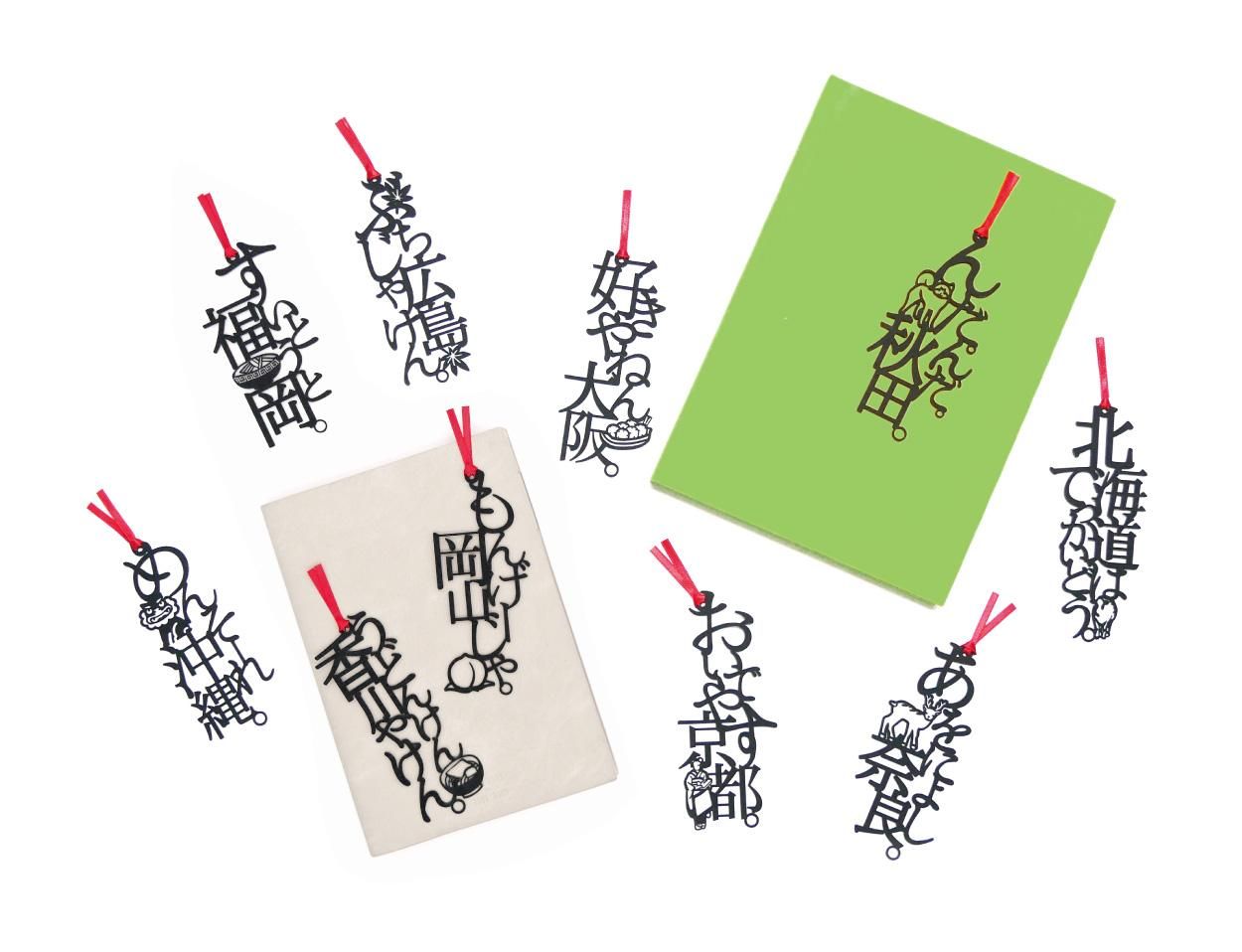
文字の47都道府県のしおり「もんげー岡山じゃ。」
桃太郎伝説の生まれたまち岡山。
日本三名園のひとつ岡山後楽園は、世界に誇る文化財です。情緒溢れる町並みの倉敷美観地区では趣ある景観が楽しめます。
桃やぶどうに備前焼、B級グルメで話題のホルモンうどんなど岡山ならではの逸品があります。
そんな「うらじゃ」な栞をどうぞよろしくお願いします。
木材パルプや綿を原料とした環境素材で、耐久性・耐水性に優れたファイバーの特徴を活かすことで、言葉がフォントごと切り取られたような巧緻で美しい『文字のしおり』のデザインが実現しています。